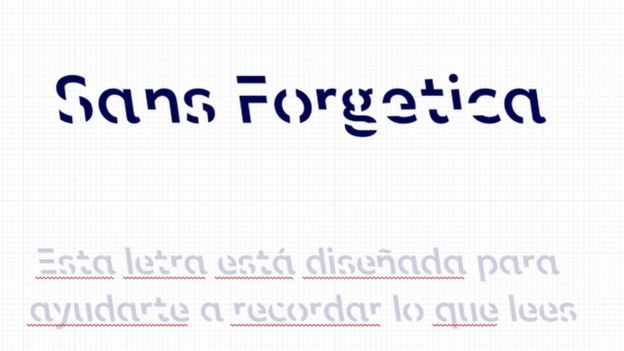
Esta tipografía te ayudará a mejorar tu memoria
Sans Forgetica es la nueva tipografía que, según diversos científicos, fue diseñada específicamente para mejorar la retención mental.
¿Te ha pasado que por más que lees algo varias veces no lo recuerdas? En la actualidad el conocimiento está en todos lados, con un par de clics puedes acceder a un sin límite de datos, pero muchas veces el ritmo frenético de vida que llevamos nos limita y el conocimiento que adquirimos se olvida.
Existen miles de técnicas para la retención mental: escribir el texto a mano, leer en voz alta, realizar esquemas después de leer, etc. ¿Te han funcionado? Quizás sí, pero también quizás no. Por ello, para mejorar específicamente la memoria, un grupo de científicos de la Universidad RMIT en Melbourne, Australia han diseñado una tipografía con la que aseguraran podrás recordar lo que lees.
“Sans Forgetica” es el nombre de esta innovadora fuente que, al ser un tipo de letra un poco difícil de leer, logrará que tu cerebro tenga que trabajar el doble para entender lo que dice, razón por la que tendrás un recuerdo más profundo de dicha información.
El presidente de RMIT Behavioural Business Lab señaló que se trataba de una herramienta buena para los estudiantes que tienen que repasar para diversos exámenes. “Creemos que es la primera vez que principios específicos de la teoría del diseño se han combinado con principios específicos de psicología con el objetivo de crear una tipografía”, añadió.
Para crear Sans Forgetica, los investigadores y académicos de la escuela de diseño de RMIT  y su Laboratorio de Negocios de Comportamiento trabajaron de la mano del reconocido tipógrafo Stephen Banham, para así probar y refinar su producto. Fueron un total de 400 estudiantes los que participaron en un experimento para comprobar la efectividad de la fuente.
El profesor titular de RMIT, Janneke Blijlevens explicó: “Los lectores a menudo miran por encima de ellas y no se crea ningún rastro de memoria. Por otra parte si una fuente es demasiado difícil de entender, la memoria no podrá trabajar correctamente, lo cual no es el caso de Sans Forgetica que se encuentra en un punto medio, en el que solo se ha agregado la obstrucción suficiente para crear retención de memoria”.